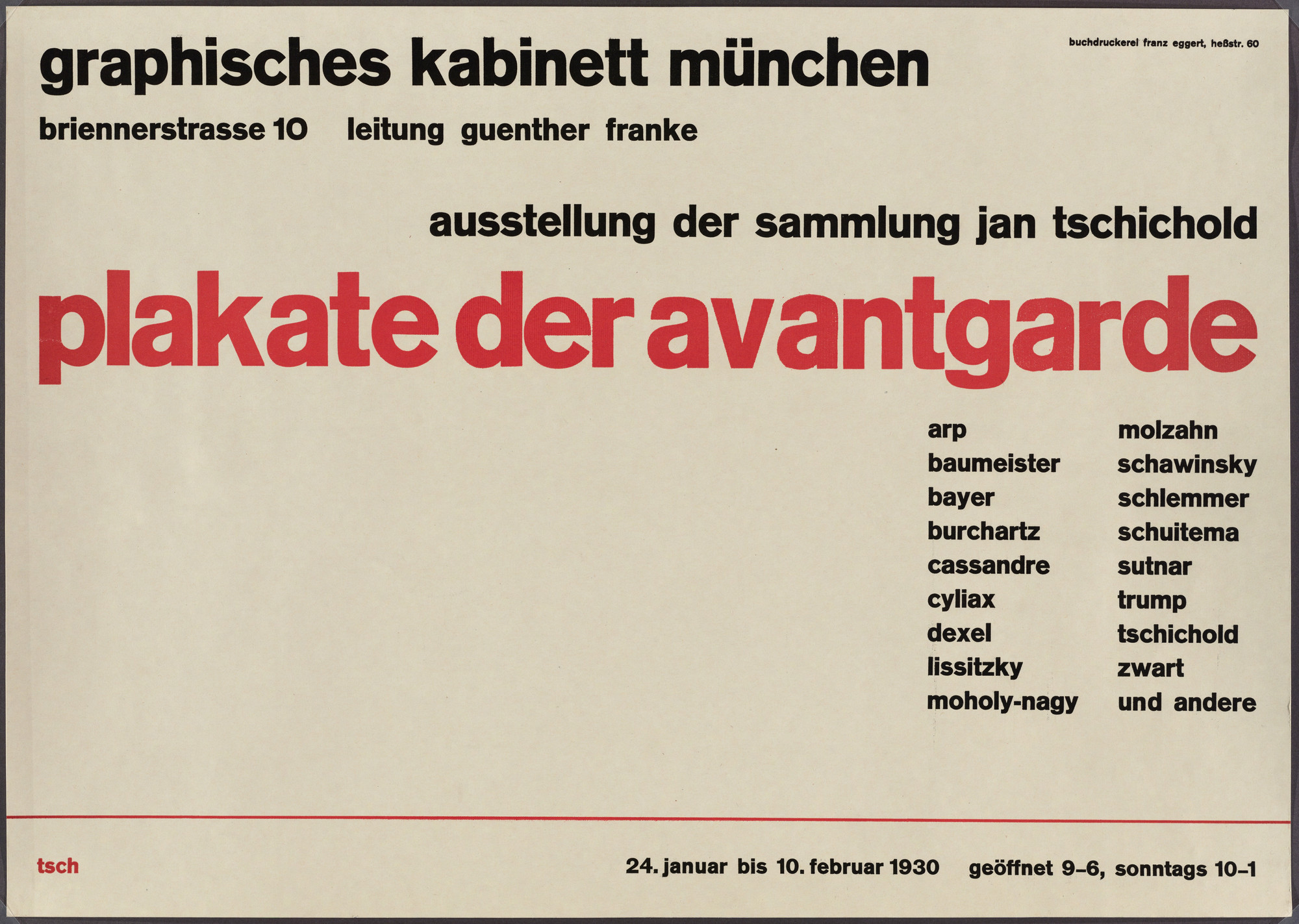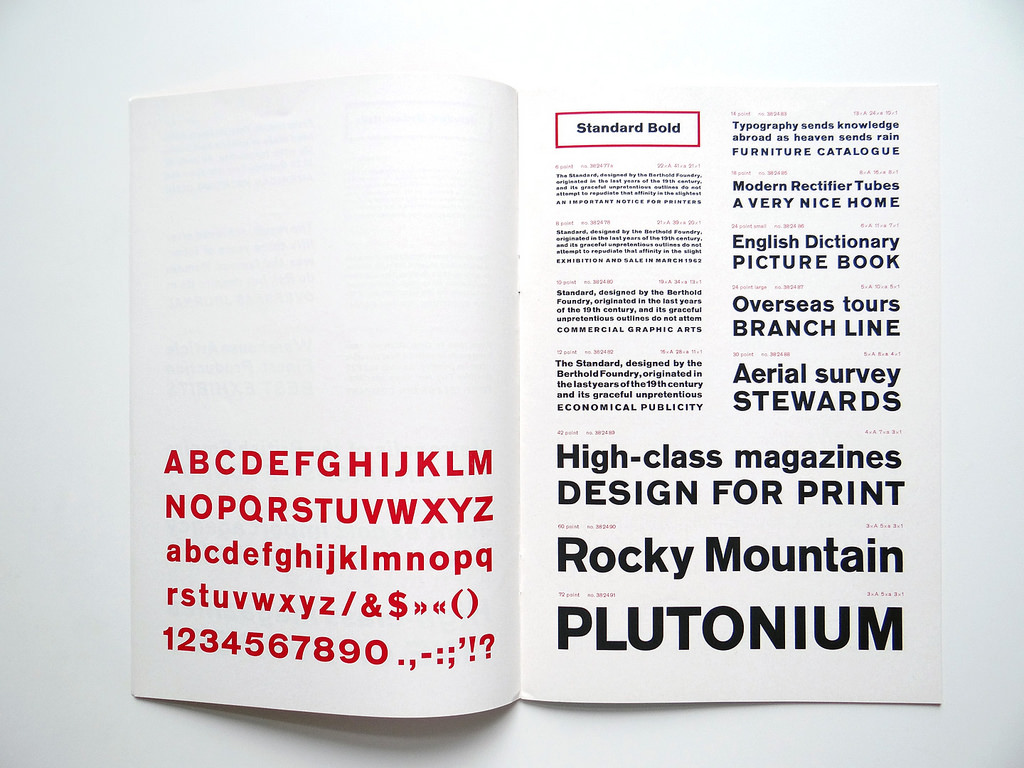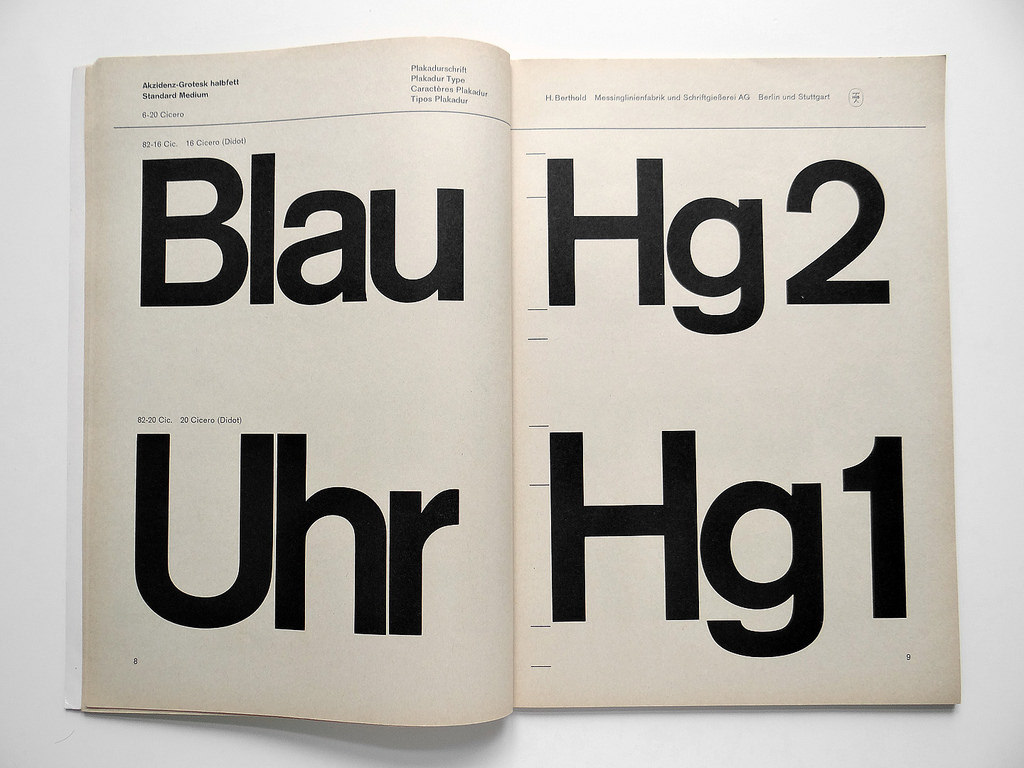
Plakate der Avantgarde: Welche Schrift wurde verwendet?
ich bin auf der Suche nach dem Namen der Schrift (rot), die hier verwendet wurde.
Das dürfte eine Akzidenz Grotesk (Black) sein.
Danke für die Antwort. Ich bin mir bzgl. der Akzidenz Grotesk nur beim 'a' etwas unsicher. Aber könnten die Unterschiede durch die Digitalisierung bedingt sein?
1930.
Unschwer zu erkennen, dass es sich bei der roten Titelschrift um einen Linolschnitt handelt.
Der kleinere Text ist aus der Akzidenz gesetzt.
Es war zu Bleisatzzeiten üblich, bei großen Schriftgraden die in der Druckerei oft nicht vorhanden waren, auf den Linolschnitt zurückzugreifen. Habe das selbst oft praktiziert.
Woran erkennt man das, zumal unschwer und bei der niedrigen Bildauflösung und ohne die Maße zu kennen? Ist das ein Plakat oder eine Postkarte? Hätte man bei Linolschnitt nicht die Wortzwischenräume denen des Satzes angeglichen?
Nachtrag: Danke für die höhere Auflösung, Michael! Ich würde meinen, man erkennt in der höheren Auflösung, daß zwei der a in avantgarde handgemacht sind, der Rest sind Holzlettern. Das erklärte auch die engeren Wortabstände und die unausgeglichenen Buchstabenabstände. Wenn jemand alles in Linol geschnitten hätte, hätte er nicht zwei a besonders schlecht geschnitten und auf den Ausgleich verzichtet. Das wäre meine Spekulation.
Nachdem am kleinen „a“ der Linolschnitt leicht erkennbar war, habe ich die weiteren Buchstaben zu wenig verglichen. Es ist tatsächlich Satz mit Linolschnitt gemischt.
Hatten die nicht genug a in Holz, dass sie sich welche dazu schnitzen mussten, oder was :-?Die letzten beiden a sehen wirklich eigenartig aus :-o
Ja, das Problem hat man gelegentlich mit großen Graden. Die Anzahl der Typen ist klein, und wenn dann irgendwo etwas in der Produktion steckt, wird es schwierig. Für die betreffende Zeile wurden fünf »a« benötigt, drei lagen wohl nur im Kasten. Dann hat man sich beholfen mit Bleischnitt (Linolschnitt kannte ich als Buchstabenersatz nicht, Bleischnitt habe ich oft gesehen und kenne es auch aus Erzählungen älterer Kollegen, daß sie viel in Blei geschnitten haben, wenn es schnell gehen sollte, vor allem geometrische Zeichen und einfache Vignetten) oder später mit Metallätzungen nach fotografischer Reproduktion. Allerdings nicht in Holz »geschnitzt«, davon habe ich jedenfalls noch nicht gehört. Aber andererseits ist in kleinen Werkstätte alles möglich, letztlich entschied der Mensch schnell und ohne Dokumentation und Facebook-Kommentar.
Genau so war es. Holzbuchstaben waren rar.
Deshalb war es üblich, einzelne Buchstaben oder ganze Zeilen in Linol zu schneiden.
Linolschnitt gehörte übrigens, zumindest in Oberösterreich, zur Ausbildung des Schriftsetzers. Bis in die Siebzigerjahre.
Es gab auf diesem Gebiet echte Meister, die Kalligrafie und das Schneiden der Schrift beherrschten.
Erwähnt sei auch, dass oft eigens entworfene Titelzeilen für Plakate in Linol geschnitten und nicht nur Satzschriften ergänzt wurden.